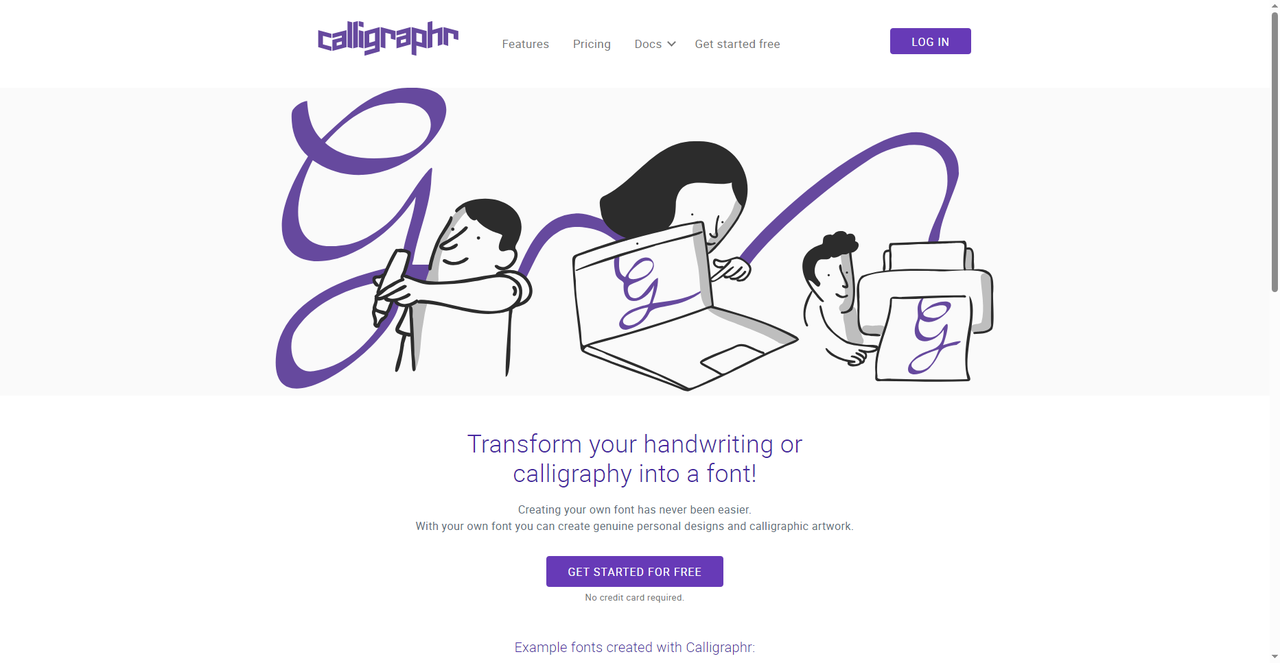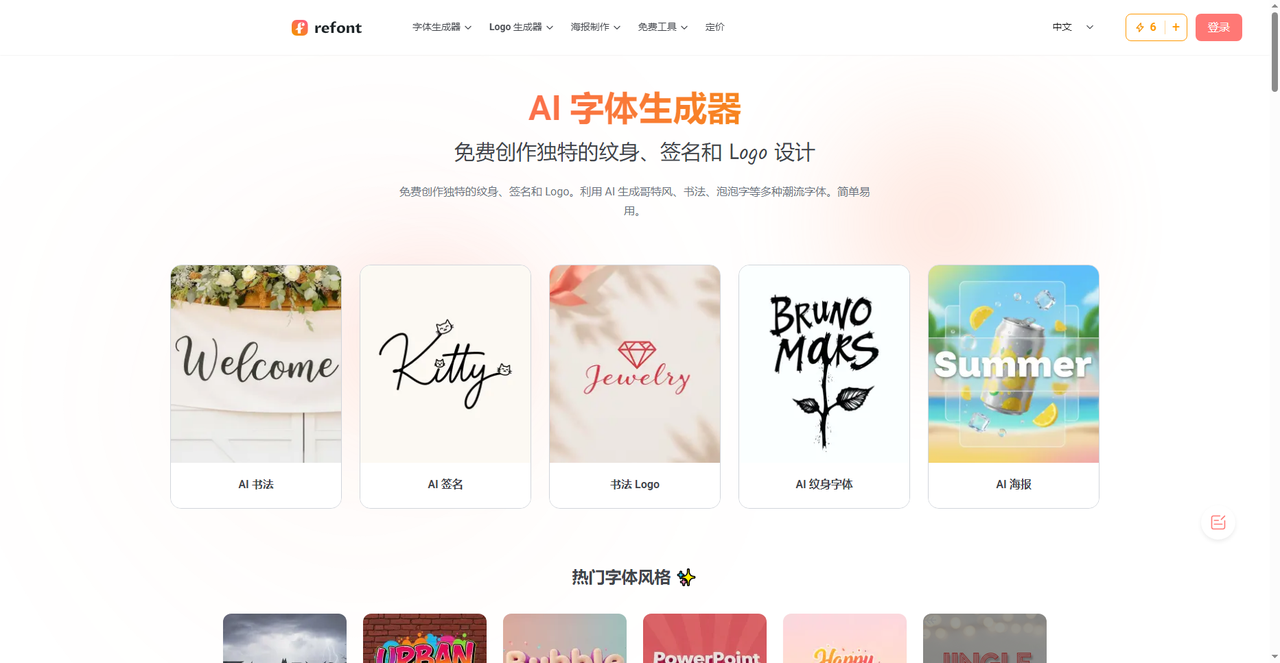
字体在线转换器推荐,普通文字秒变花式字体
现在AI渗透到了各行各业,给我们的工作带来的极大的便利,其中也包括了设计行业,以前如果想要一款字体的特殊效果肯定是要手搓的,但是现在的话只需要通过多字体在线转换器就可以办到,具体操作为输入文字,点一下,秒变各种花式字体,复制粘贴就能用。千万不要再当原始人啦,从现在开始,可以试试我这篇文章推荐的5 个字体在线转换器,每个都能够让你拥有漂亮的特效字体,喜欢的话可以收藏!
很多人知道字由是字体管理神器,上万款字体库内容丰富,字体齐全。但你可能不知道,字由的“AI字体”功能,其实也能当在线转换器用。你不需要下载任何字体,打开网页就能把普通文字转成带特效的艺术字。
- 第一步:打开字由官网,找到【AI字体】。在搜索框里输入你想要的效果,比如“霓虹”“金属”“国潮”“手写”“3D”,系统会筛出对应的模板。每个模板都是一个现成的“转换效果”——你输入普通文字,它输出带特效的艺术字图片。
- 第二步:选一个模板,点击“做同款”,把模板里的文字换成你自己的,点“立即生成”,等20-30秒,就能拿到一张高清艺术字图片。下载透明背景PNG,直接拖进PS、Canva、剪映里用。
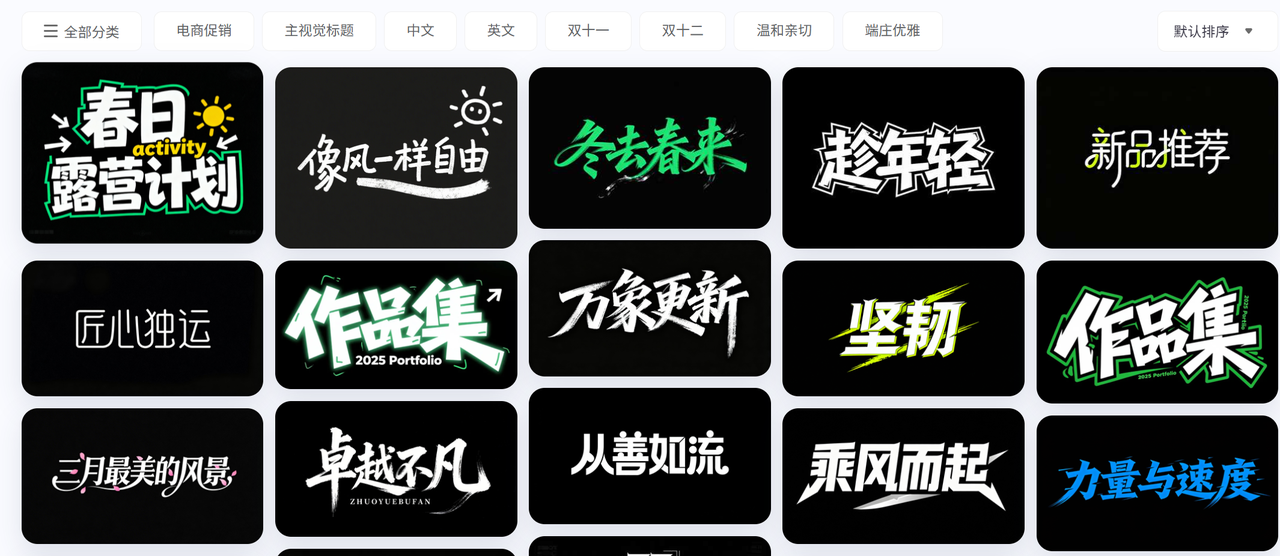
只需要简单的两步就可以完成,过程甚至不超过五分钟,这和传统的在线转换器不太一样——它不是给你可复制的Unicode字符,而是直接生成图片。但如果你是要做海报、封面、视频标题,图片格式反而更方便,因为带特效、带光影、带纹理,不是单纯的字母变形。
字由的AI字体模板库非常丰富,按场景分好了类:
- 霓虹灯管:带玻璃管质感的霓虹字,适合音乐海报、酒吧招牌
- 金属质感:拉丝不锈钢、铬金属高光,适合科技产品、工业风
- 国潮书法:水墨晕染、毛笔飞白,适合国风海报、传统文化
- 水彩晕染:边缘模糊、颜料渗开,适合文艺封面、手账标题
- 3D立体:带厚度和透视,适合游戏标题、品牌Logo
- 节日喜庆:大红底色、金色描边,适合春节、促销活动
而且除此之外,字由本身也有海量的免费商用字体库。如果你想在微信、微博里发花式海报,可以直接用字由的字体。我最常用的是字由芳华体,是一个温柔手写风。
其实严格来说,字由的强项不是生成可复制的Unicode花式字符,而是生成带特效的艺术字图片。但考虑到使用场景不同,字由更适合做设计图,而下面的几个工具更适合直接复制粘贴到社交媒体。
2、Calligraphr
这个网站叫Calligraphr,它的功能和传统在线转换器不一样——它不是把你输入的文字转成花式字体,而是让你上传自己的手写样本,生成属于你自己的字体。你可以把每个字母写在纸上,拍照上传,或者用绘图板在电脑上画,然后Calligraphr会把它们拼成一套完整的字体文件(TTF或OTF)。下载安装后,你就能在Word、PS里用你自己的手写体打字了。适合谁用?漫画家、手账爱好者、想做个人品牌的设计师。比如截图里有用户评论说:“我用Calligraphr把我的笔迹变成了字体,省了我画漫画的时间。”还有人说:“超级便宜,超级好用。”免费版可以创建少量字符,付费版可以解锁更多。如果你想要独一无二的专属字体,这个工具很合适。
3、refont
refont,是一个中文AI字体生成器。它的首页展示了几个主要功能:AI书法、AI签名、书法Logo、AI纹身字体、AI海报。你只需要输入文字,选择风格(比如“哥特风”、“书法”、“泡泡字”、“潮流字体”),AI就能生成专业级的设计。比如你输入自己的名字,选“AI签名”,它会生成好几个签名方案供你选。它完全是免费的,适合需要个性化签名的用户,或者想给纹身找字体参考。生成的结果是图片格式,可以下载保存。
4、Cool Text Generator
这个网站的名字就叫“Cool Text Generator”,界面很简洁。输入文字后,它会生成多种酷炫的文字效果,比如带阴影、带轮廓、带渐变等。每个效果下方都有“Copy”按钮,点一下就能复制,直接粘贴到社交媒体、论坛签名、游戏昵称里。它和前面几个不同:不生成图片,只生成可复制的Unicode花式字符。所以发到微信、微博里,对方也能看到同样的效果。适合想快速让普通文字变特别的普通用户。
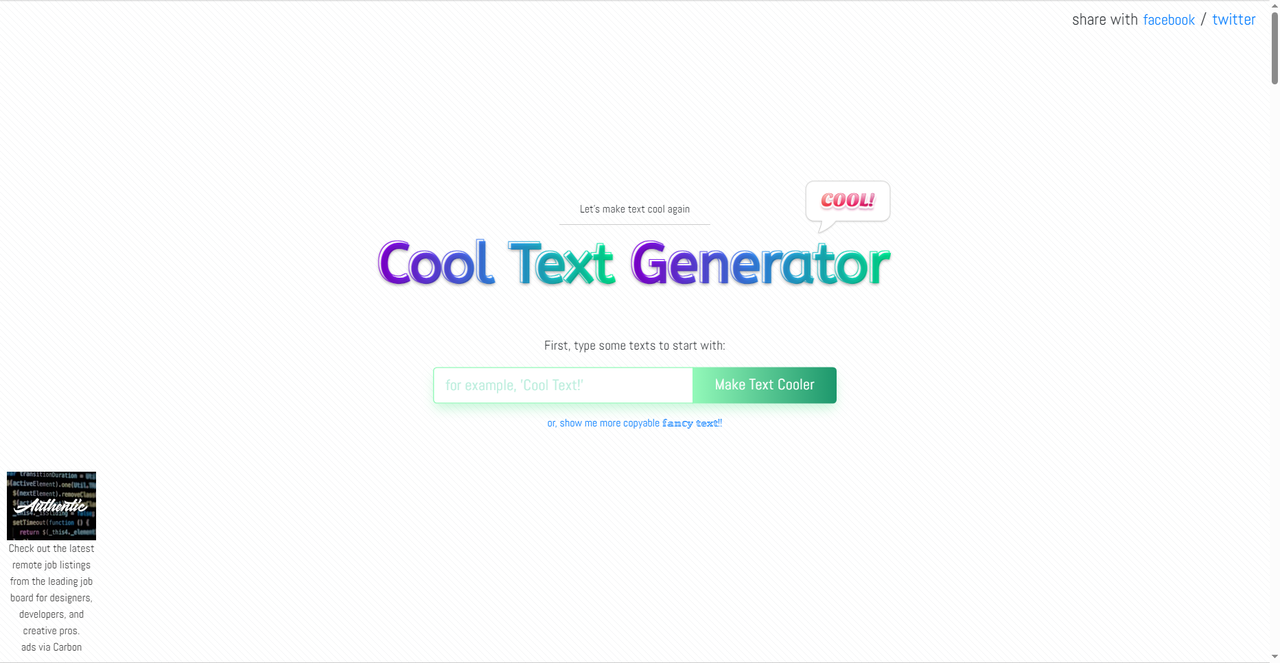
5、Font Generator
最后一个网站是一个功能强大的字体在线转换器,它提供了184种字体样式。左侧有搜索框,可以搜“Cursive”“Bubble”“Gothic”等关键词。右侧按类别分组,比如“Mathematical & Scientific”有15种样式,包括Mathematical Bold、Mathematical Italic、Mathematical Bold Italic,还有Script / Cursive、Bold Script等。输入文字后,每个样式旁边都有“Copy”按钮,点一下就能复制。样式非常多,从数学符号到花体到气泡字,几乎覆盖了所有Unicode 花式字符。适合需要大量选择、喜欢尝试不同风格的用户。
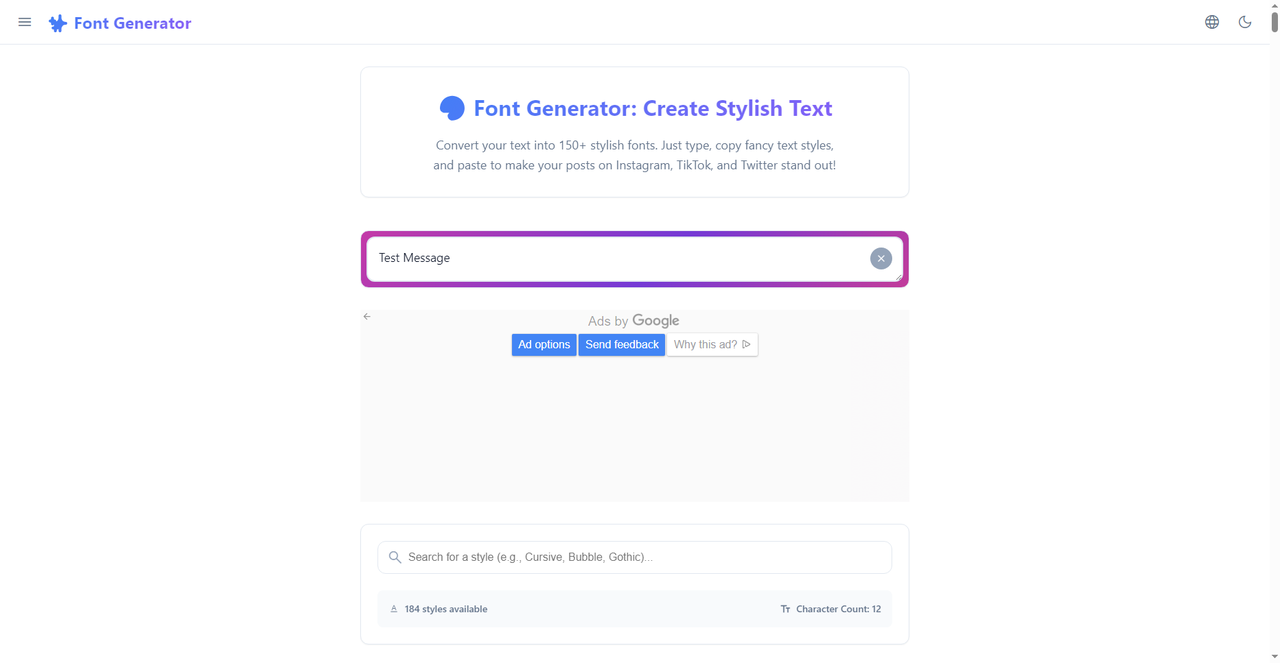
这几个字体转换器都有自己的特色,Calligraphr 把自己的手写体变成字体;refont 用AI生成签名、纹身字体;Cool Text Generator 让文字变酷;Font Generator 有150+ 种样式,分类超细。但如果你需要的是带特效的艺术字(霓虹、金属、国潮),字由的AI字体功能更合适。它生成的是高清图片,直接用在设计里,不用再调效果。如果你也想让普通文字变得更特别,不妨从字由开始试试。